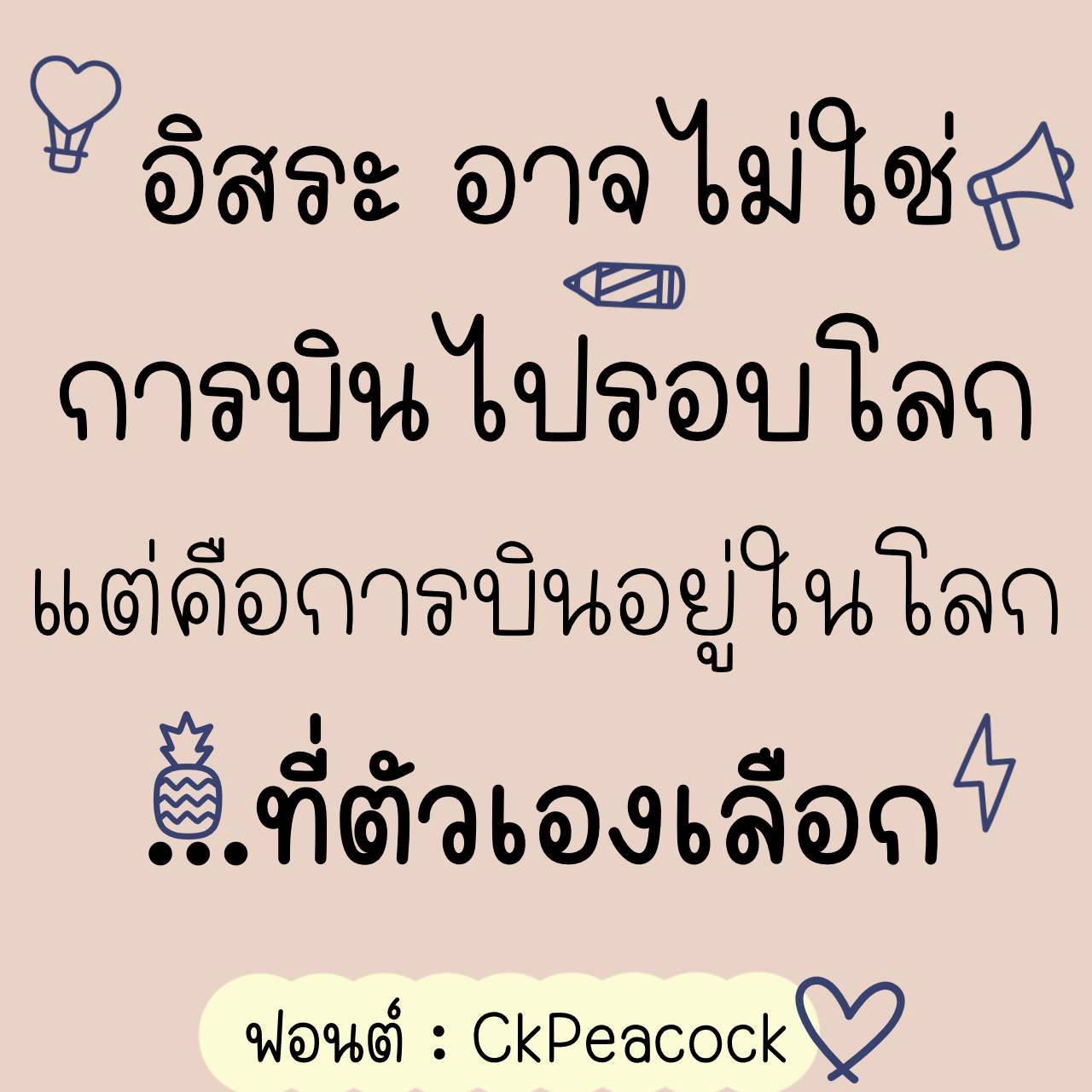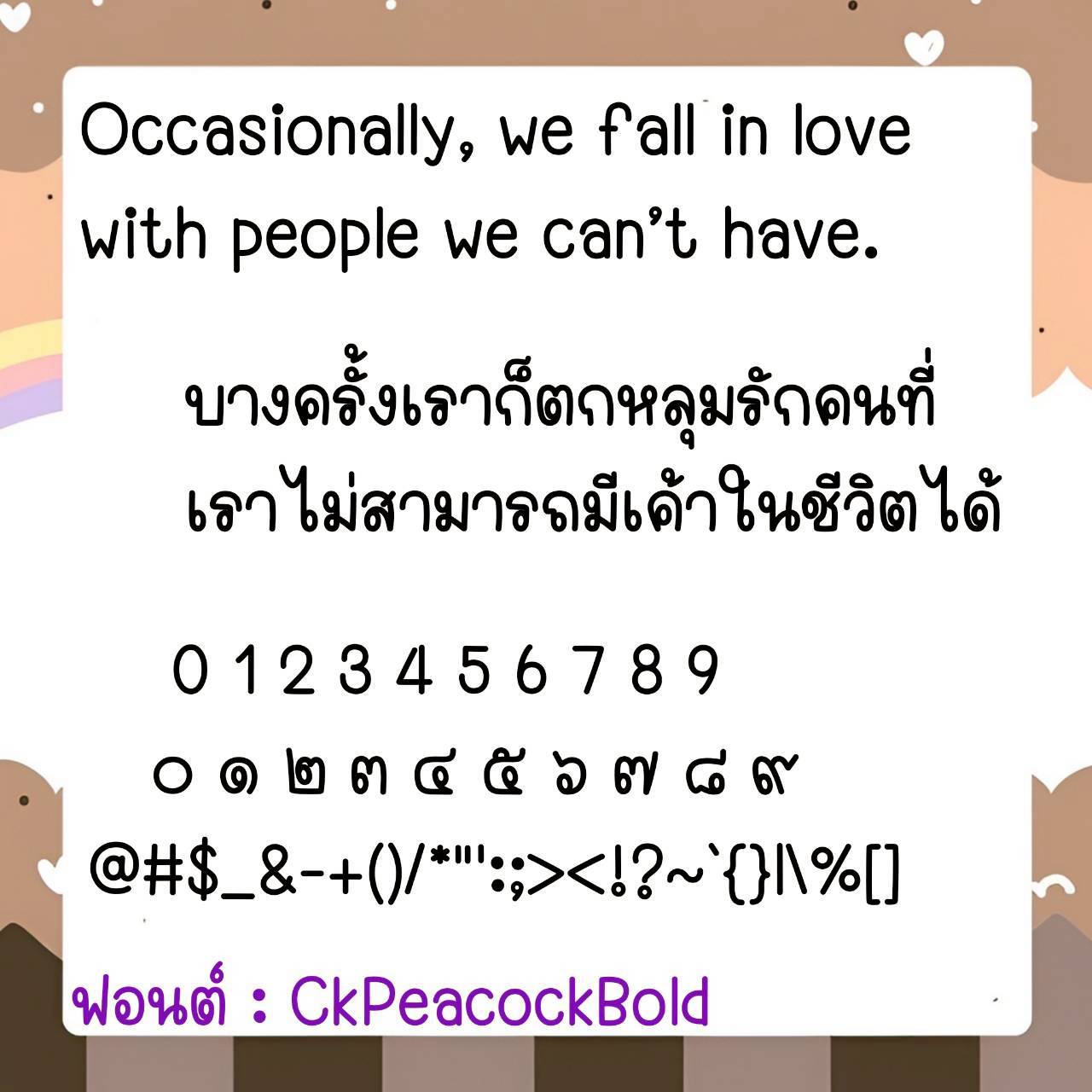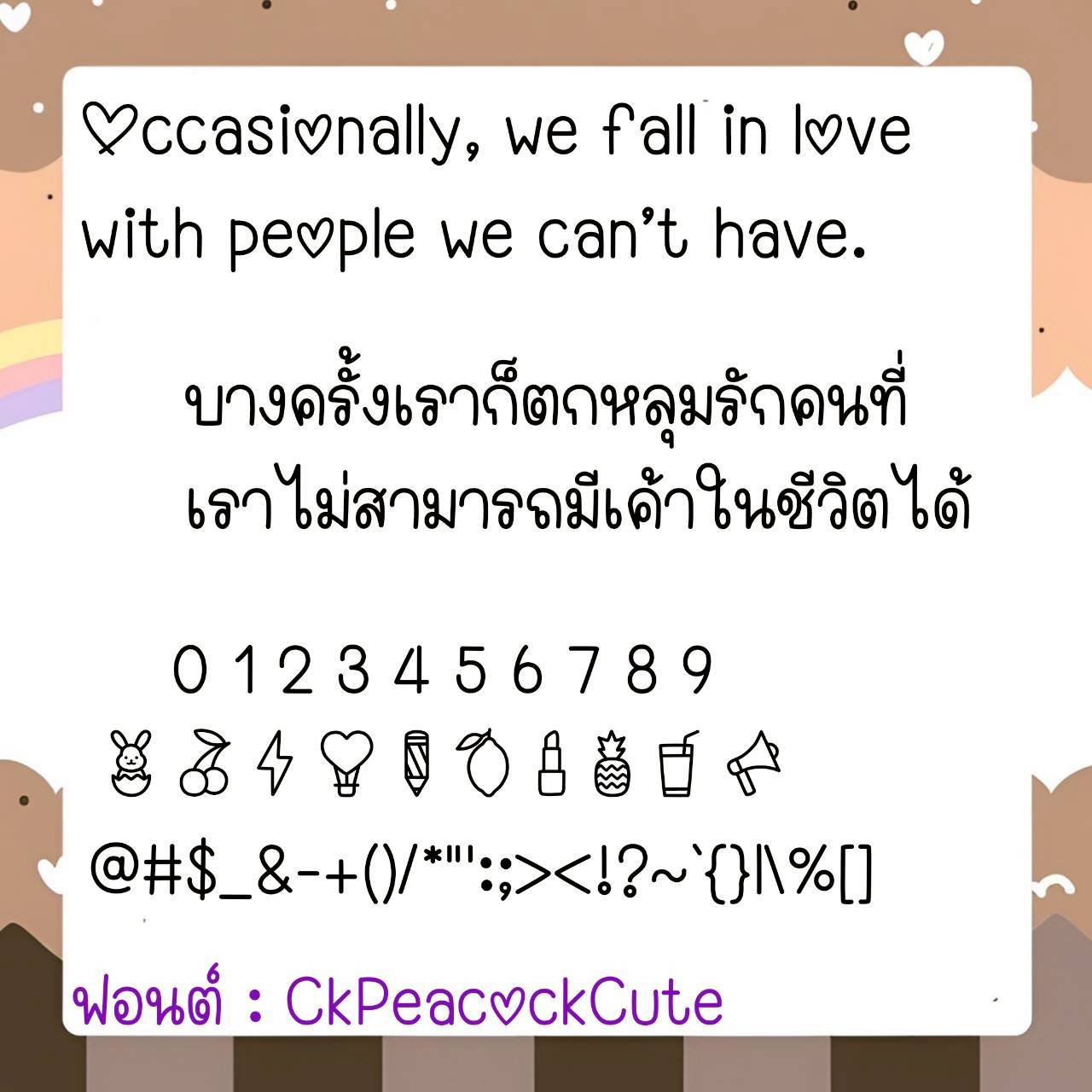
Font CkPeacock
ชื่อสินค้า : Font CkPeacock 💙
🔸 ฟอนต์ลายมือตัวอ้วนปุ๊กปิ๊ก หัวฟอนต์มนๆยาวๆ ตัวฟอนต์มีความน่ารักกรุบกริบ อ่านง่ายสบายตา และยังมีไฟล์อิโมจิน่ารักๆ ที่ใช้แทนเลขไทยให้ด้วยค่ะ 🥰💙
🔹 A chubby, cute handwritten font with a long, rounded font head. The font is cute and easy to read. There is also a cute emoji file that can be used instead of Thai numbers. 🥰💙